高考出现的“神仙字体”,迅速走红网络,网友:这手堪比打印机!
每个学生从小到大都要经历无数场考试的磨炼,大大小小的考试犹如战场一般。“久经沙场”的学生们对于考试当中的答题技巧或是答题思路早已烂熟于心,五花八门的“套路”也都能熟练破解。在考场上的书写“字体”上,每个学生都有属于自己的小技巧。
早在几年前网络上飞速走红的“衡水体”让无数在校生羡慕不已,学生之间掀起了一阵阵买字帖练字的狂潮。很多学习基础不牢固的学生很难在答题点上获得较高的分数,于是想要通过练习出赏心悦目的字体来博得改卷人的欣赏,巧妙使用“提高印象分”的小妙招。从改卷人的角度来看,一天面对成千上万份试卷,在高强度的工作状态中,眼前突然出现一份清新秀丽的文字,心情定会舒爽万分,自然就会为这个考生多给点卷面分。
特别是对于初入高中的学生来说,尽早开始练习一手好字是很有必要的。练成一手好字并不是一蹴而就的事情,练字是个漫长的过程,但愿意花费三年的时间每天练习一点点,字体也会每天好看一点点。将日常写作业的过程当作练习字体的绝佳机会,充分调动自己的练字积极性。“养兵千日用兵一时”,等到了高考那天将最好的字体展现在考场上,为自己扎实的知识基础进行美观的字体加持,最后的成绩一定差不到哪里去!那么到底什么样的字体在考场上最受欢迎呢?
高考大军的队伍中充斥着各式各样的字体,行书、楷书、草书等纷纷上阵。其中,最能获得阅卷老师青睐的便是标准的“印刷体”了。“印刷体”正如其名,学生能够将手写的字体写得更印刷在书本上的字体一般,干净工整,清晰爽目。一行行清新秀丽的“印刷体”像刻在答题纸上一样,与答题过程和谐相融,一气呵成。没有哪个老师会不喜欢这样的字体。
上图中就是一位学霸答题纸上的“印刷体”,字里行间没有任何拖泥带水、歪曲忸怩的部分,特别是字与字之间的间隙也控制得十分巧妙,就像从打印机上打下来的文字,排版的美观度、字体的整齐度都很高。连批卷老师都说:“这样的卷子看了都不忍心扣分!”。这份试卷还被老师在班级上进行传阅,让同学们都向这样的字体好好学习,不断提升自己的书写水平。
有同学很快就对此进行反驳,考场上的时间那么紧张,考试上的精神状态也很紧绷,有时候要在大脑里加工很久之后才能将答案呈现在考卷上,同时下笔的速度一定要跟得上大脑思考的速度。在这么匆忙的答题状态下还能将好看的字体书写出来实在有一定的难度。正如小编在前面提到的,练字是个长久的事情。好看的字体要付出大量的练习才能够。从小就养成练字的好习惯,一定会在将来有不小的优势!
正如大家都听说的那样,阅卷老师每天的阅卷工作量是很大的,面对着扫描在电脑屏幕上的文字,视觉上的疲劳是难以避免的。在众多试卷当中,突然发现一份赏心悦目的字体是件极其愉快的事情。就像在荒漠上走了很久的人终于看见了一片绿洲一样。看到如此娟秀大方的字体,试卷的卷面分一定少不了。有些考生认为,不就是那一两分的卷面分值嘛,我完全不在乎。这样的心理是极其不成熟的,高考毕竟称得上是千军万马横过独木桥,就连一两分的竞争也是极其激烈的。甚至在全国、全省的排名中,一分就能相差好几万人。想要顺利进入自己心仪的大学,必须分分必争。千万不能“差之毫厘失之千里”!
下面这张图正是出自衡水学霸之手,看到这篇作文的字迹的人,都忍不住称赞几许。“这简直就是打印出来的字体吧!这字体的大小完全一样,一撇一捺都精致极了!真不愧是从衡水中学培养出来的人才!”不得不说衡水中学,在培养高考人才方面很有自己的“一套”。不少学生都顺利进入清华、北大入读,衡水中学可以说是功不可没。衡水中学不仅在学生管理制度、教学水平等方面占据了独特的优势,而且在字体规范上也极其的严格。不少学校只注重对学生知识的传授,而忽视了知识输出载体的美观性。练就一手好字不仅在高考上有重要的优势,而且还是收益终身的好事。
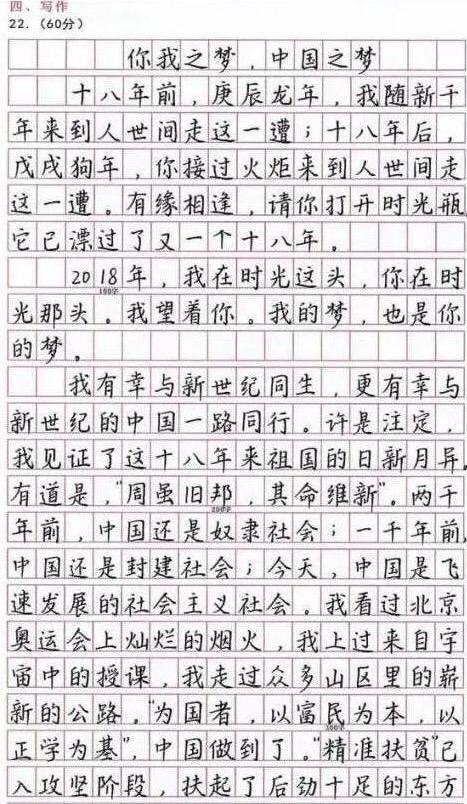
“印刷体”常常能够获得阅卷人的青睐,虽然书法界并不提倡“印刷体”。那“印刷体”到底是什么字体呢?练习哪种字体才能写得像“印刷体”一样呢?
楷书也叫正楷、真书、正书。由隶书逐渐演变而来,更趋简化,横平竖直。《辞海》解释说它“形体方正,笔画平直,可作楷模”。这种汉字字体端正,就是现在通行的汉字手写正体字。如果你能开始以楷体为模板进行练习,很快就能像标准整齐的“印刷体”靠拢。
“印刷体”不像书法界的楷体有一定的艺术性、美观性,但两种字体之间的相似度还是很高的,能练就好楷体字体一定会赢得阅卷人的眼前一亮。相反,一定不要尝试个性很强的“自我风格”的字体,面对考生龙飞凤舞的草书时,阅卷人的心情一定是灰暗的,因为有些字识别起来都是件难事。你让阅卷人心情不愉快了,那卷面分是一定拿不到的。有些甚至直接按错别字、看不清来算,整个试卷下来因为书写问题扣下不少分实在不值得。稳妥起见,就选楷体练习吧!
衡水中学都求学生们写这种整齐规范的字体,自然有他们的道理,咱们还有什么理由赶紧安排上呢?
总而言之,人们常说“字如其人”,一手工整漂亮一定能为自己带来不少优势。学无止境,练习不休。我们在练字的道路上还要越走越远,不可懈怠。除了练就自己的一项本领外,还能身体力行地传承汉字这一中国优秀传统文化,凭借自己的力量不断发扬光大。